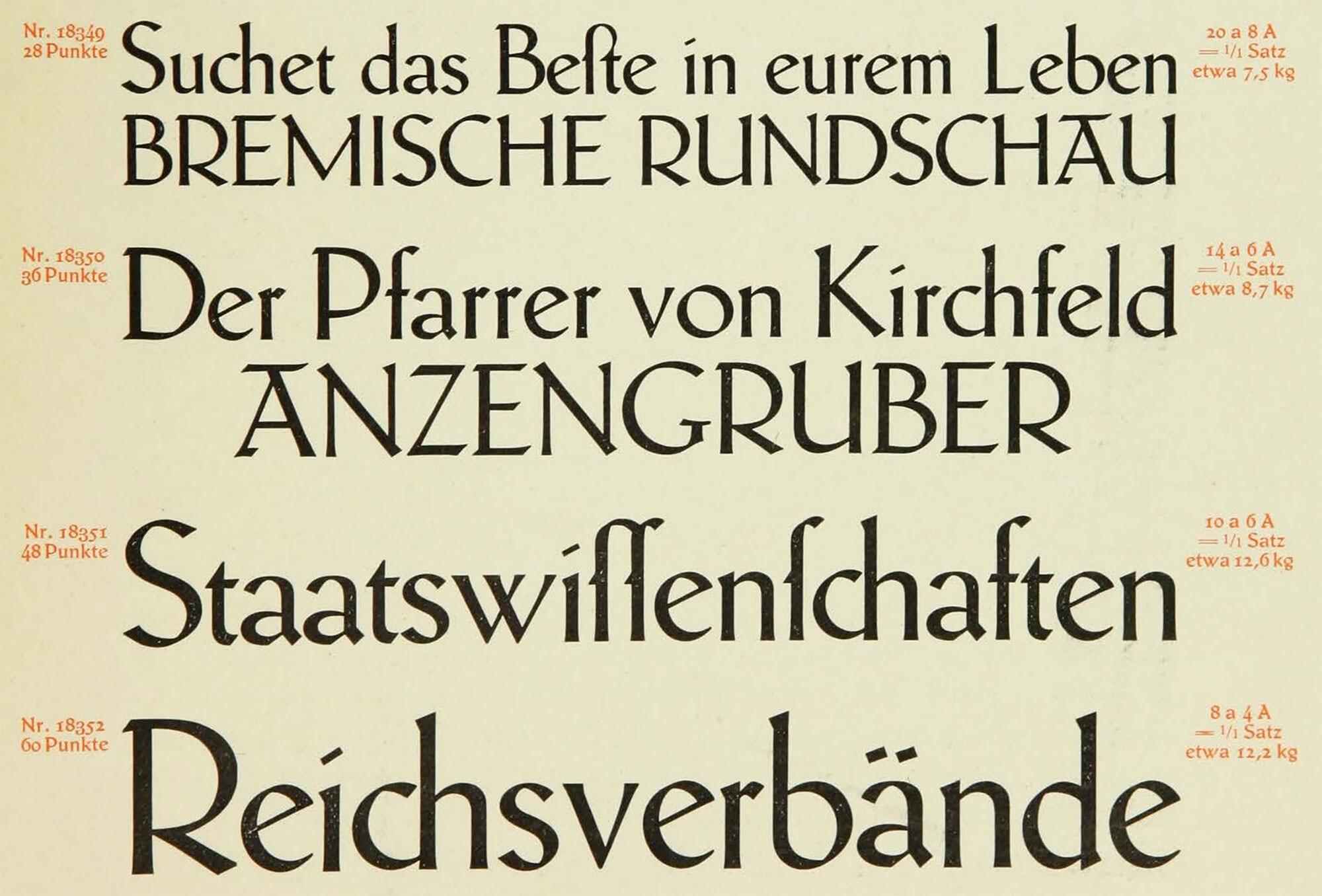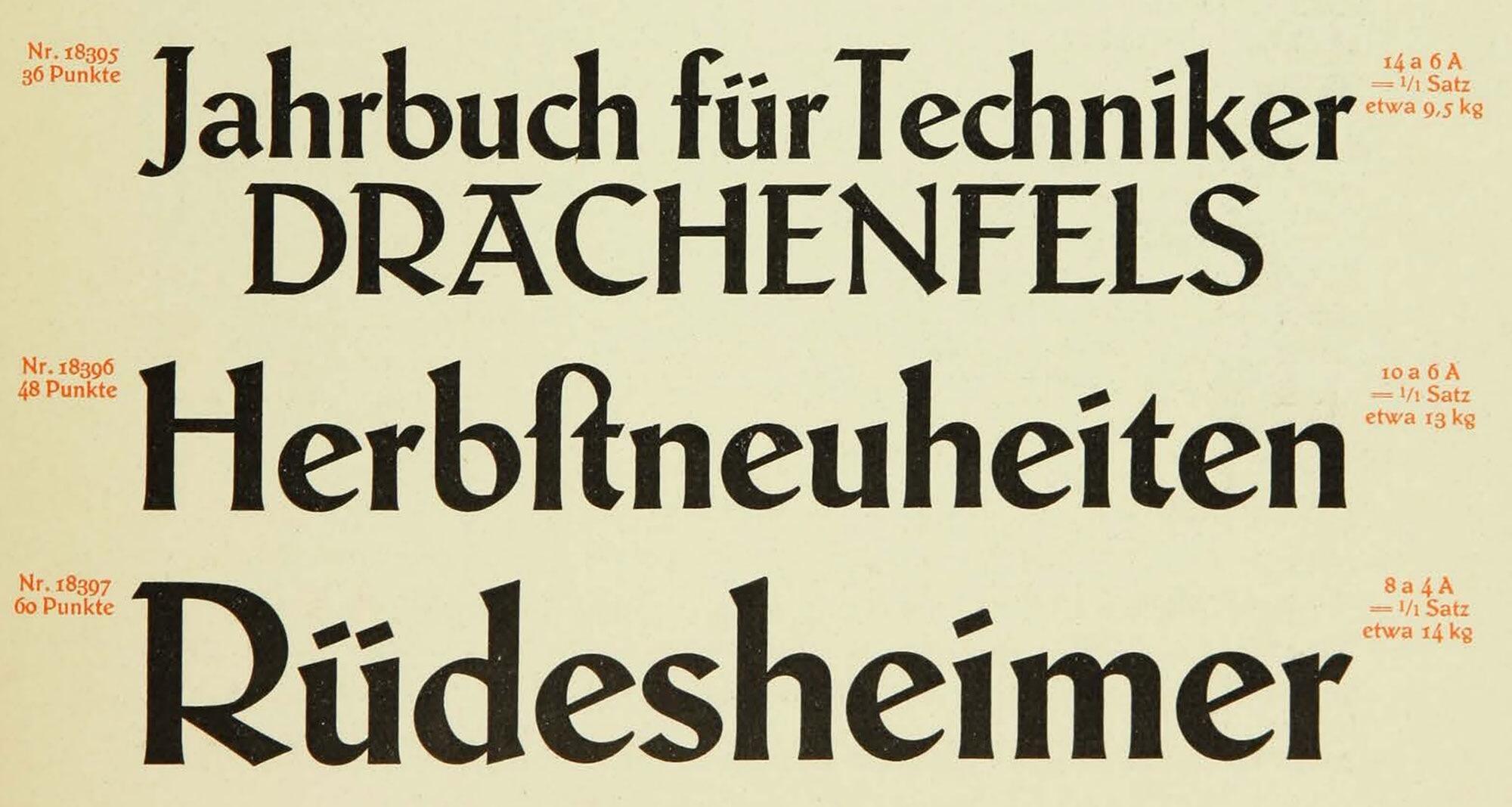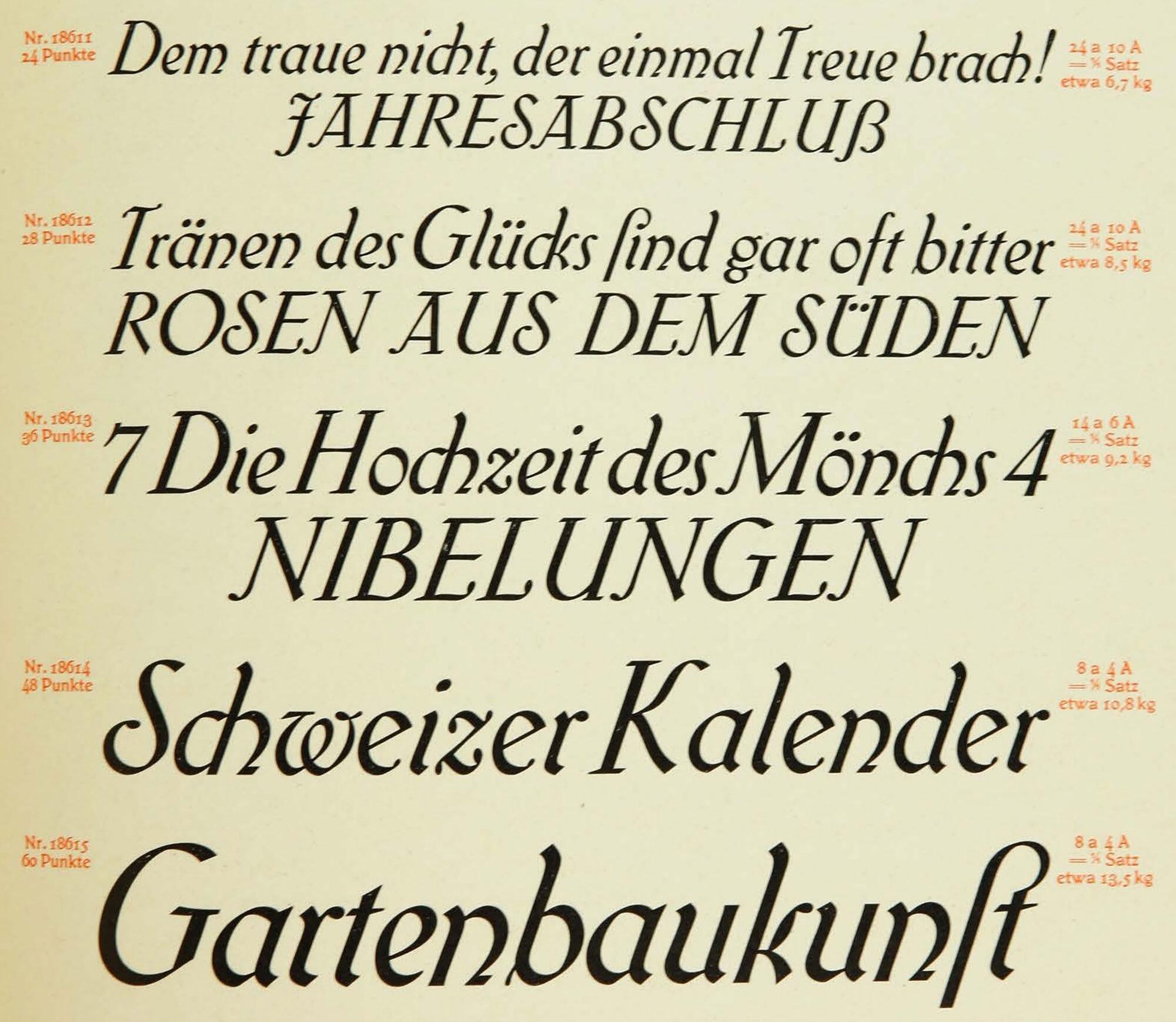
- 1919
- Antiqua humanistisch
- Versaleszett:
- enthalten
Die Schneider-Latein von F.H. Ernst Schneider erschien laut verschiedener Quellen zwischen 1916 und 1919 als »Schrift für Bücher und Gelegenheitsdrucke« bei der Schriftgießerei Schelter & Giesecke in Leipzig. Die Schrift wurde bis Anfang der 1920er-Jahre auf insgesamt drei Schnitte ausgebaut: Schneidler-Werk-Latein, Schneidler-Antiqua halbfett und Schneidler-Schrägschrift. Zum Zeichenvorrat in allen Schnitten gehörte auch ein großes Eszett.
Eine umfangreich ausgebaute Digitalisierung von Lena Schmidt erschien 2019. Die Familie verfügt über neun aufrechte Schnitte mit 956 Glyphen in erweiterter lateinischer Belegung (einschließlich Kapitälchen).